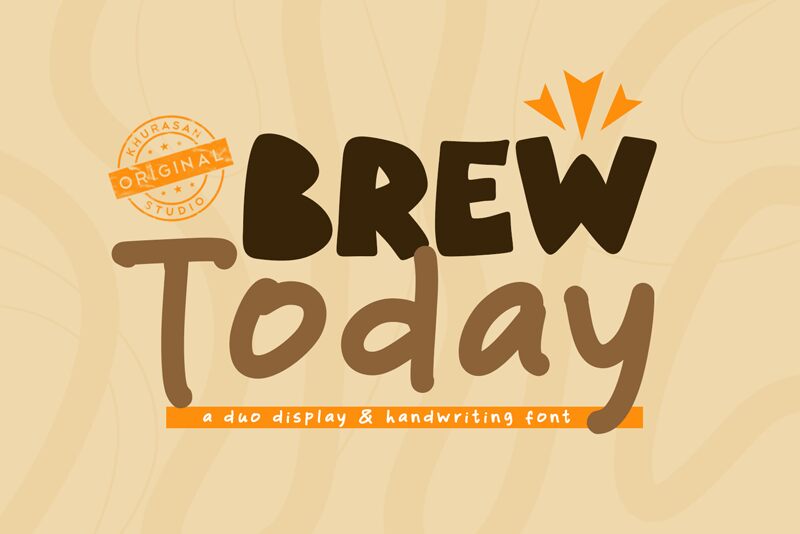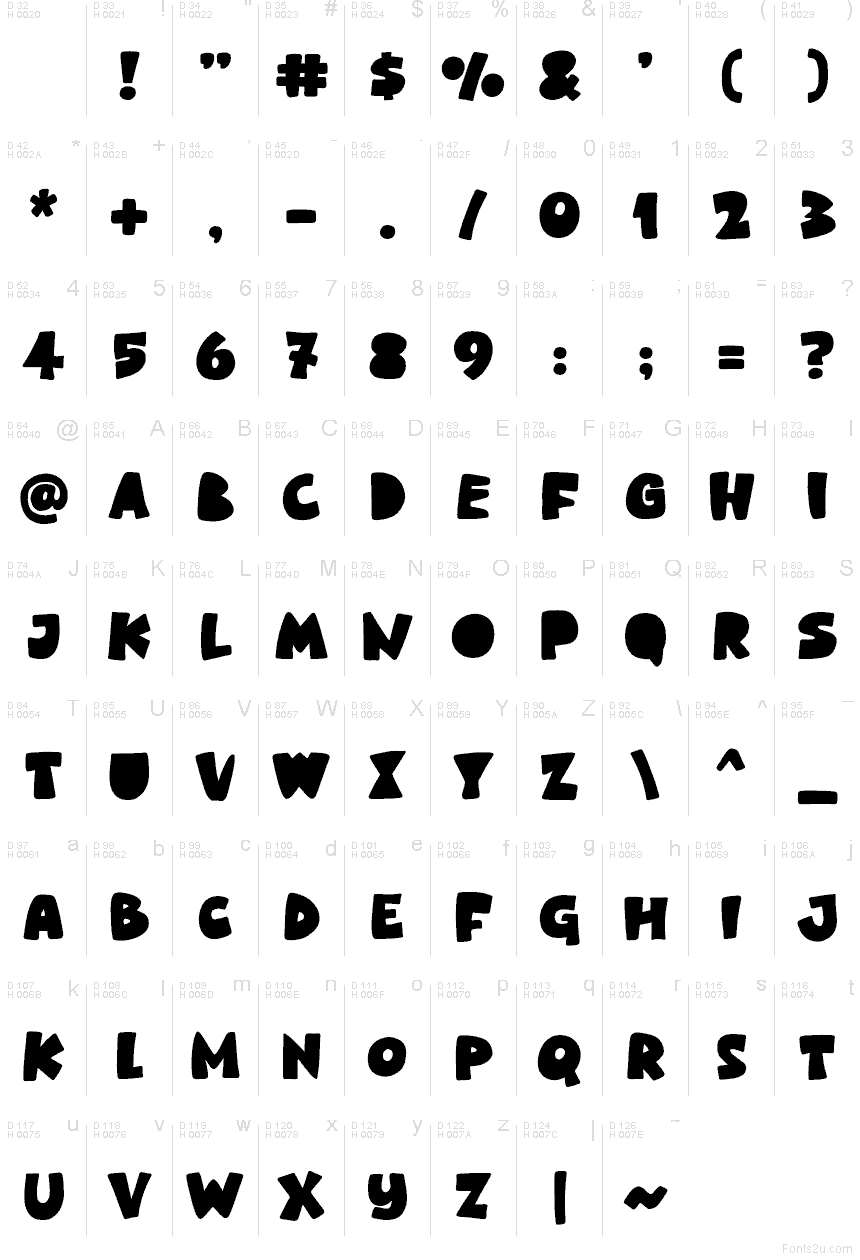
Brew Today di Khurasan è un font in stile cartoon gratuito con lettere ampie e irregolari e una silhouette allegramente intagliata a mano. Forme esterne arrotondate incontrano intagli netti e angoli improvvisi, creando un vivace mix di morbidezza e mordente. Le larghezze mutevoli conferiscono alla scritta un tono piacevolmente fuori dagli schemi.
Il suo spirito da fumetto si adatta all'editoria per bambini, al packaging di snack e ai manifesti per eventi giocosi. Le forme piene possono anche diventare parte di grafiche incentrate su mascotte o illustrazioni per merchandising, anziché fare da sfondo come caratteri neutri. Per i marchi giovanili, i contorni irregolari creano uno stile di logo memorabile.